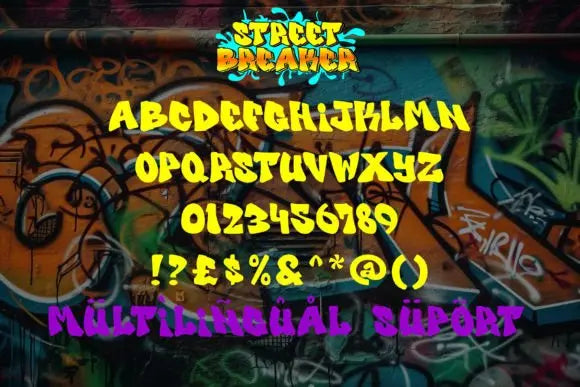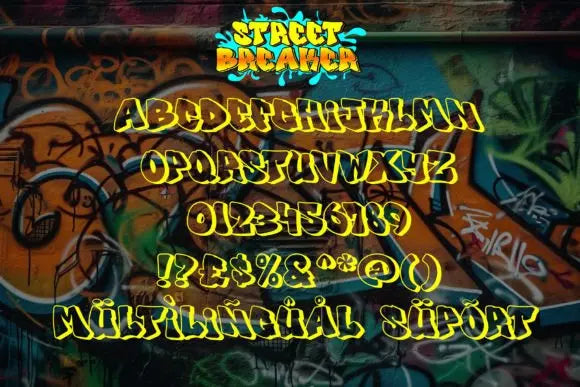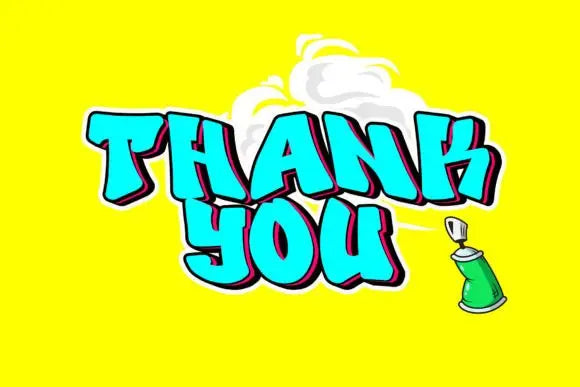
Fuente Street Breaker
Street Breaker es una fuente de graffiti con bordes afilados, lo que la convierte en una opción perfecta para varios proyectos de temática callejera. Con su estilo moderno y dinámico, esta fuente agrega un ambiente vanguardista y urbano a tus diseños. Los bordes afilados le dan un aspecto atrevido y llamativo, asegurando que su tipografía se destaque con un estilo distintivo y rebelde. Dale un toque de actitud callejera a tus proyectos con la fuente Street Breaker.